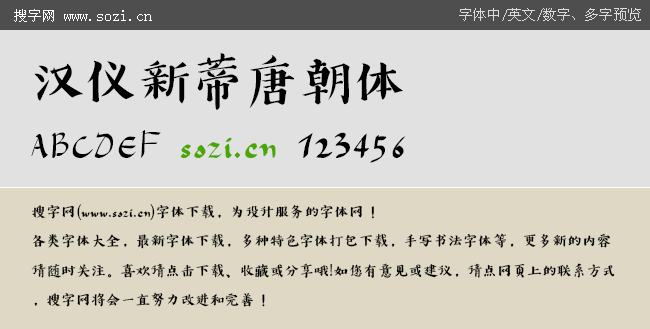
漢儀新蒂唐朝體
搜字網(wǎng)提供一款漢儀新蒂唐朝體中文藝術(shù)字體下載,漢儀新蒂唐朝體,是一款融合了雕刻與書(shū)法的字體。在古代手抄過(guò)渡到印刷術(shù)時(shí)代的過(guò)程中,字體在雕刻的技術(shù)下試圖保留毛筆書(shū)法的特點(diǎn),當(dāng)這兩種手法的相碰撞之后,便賦予了字體幾分獨(dú)特的氣質(zhì)感。可用于海報(bào)設(shè)計(jì)、包裝設(shè)計(jì)、廣告設(shè)計(jì)、網(wǎng)頁(yè)設(shè)計(jì)等。